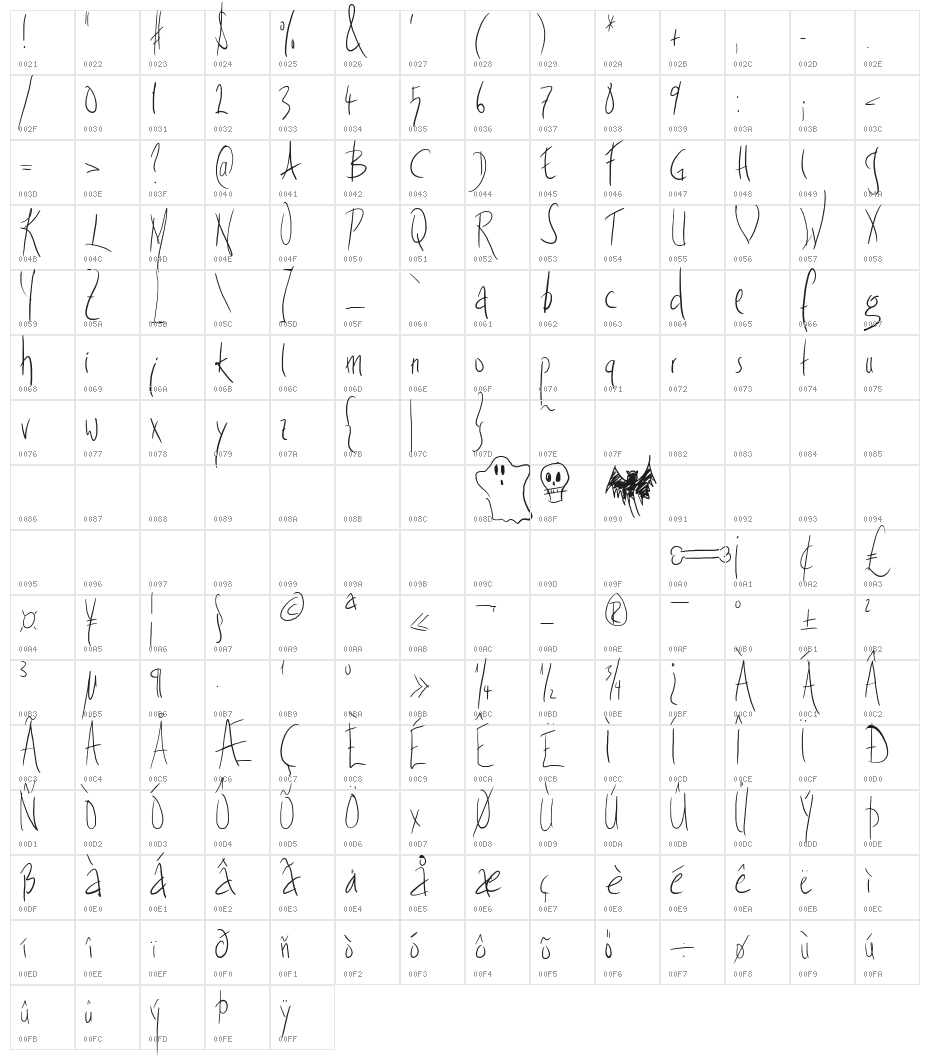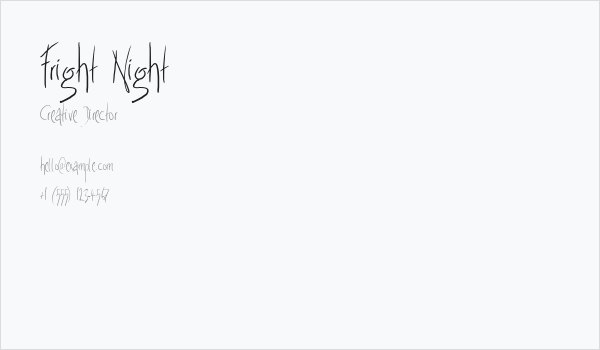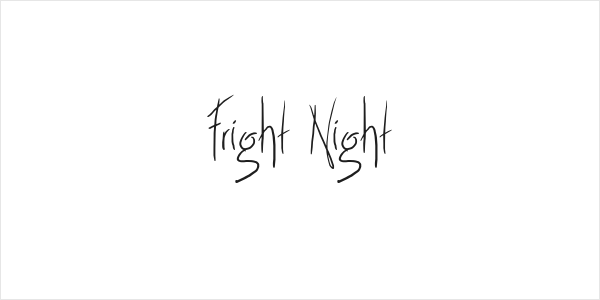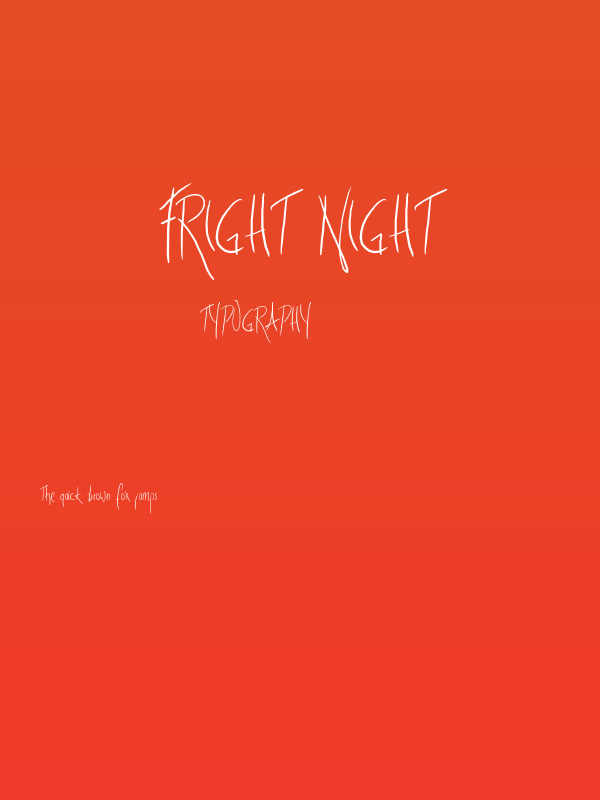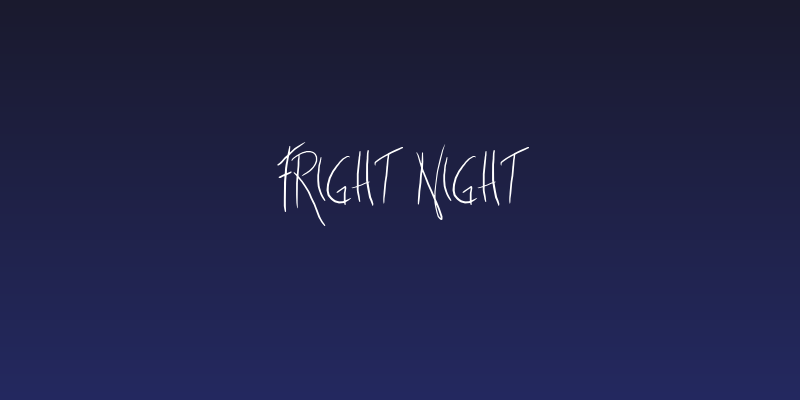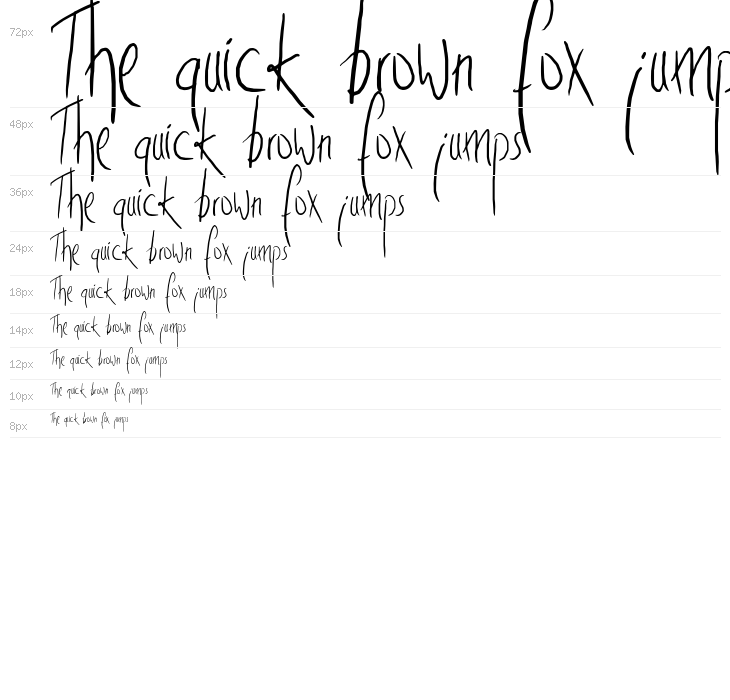
Fright Night Font
| Caso d'uso | Headlines, Logos, Thematic Designs |
| Progetti proposti | Perfect for Halloween-themed designs, horror movie posters, haunted house flyers, or any project requiring a spooky, playful touch. |